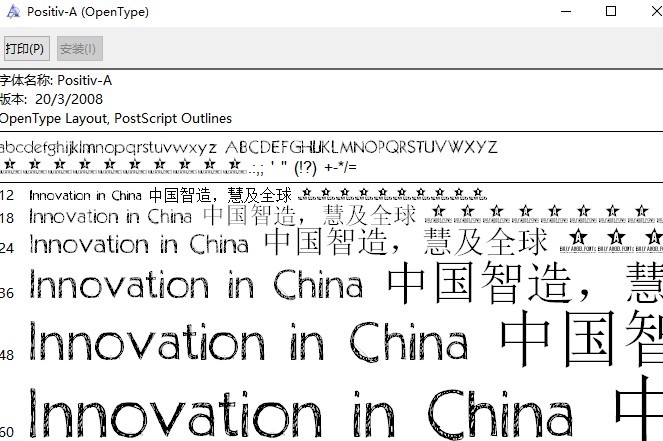
positiva字體是一個(gè)比較有個(gè)性的英文字體。輸出的字體帶有一層浮雕效果,看上去非常大氣。這款英文字體無論是用來設(shè)計(jì)還是排版都很合適。兼容多種主流的計(jì)算機(jī)操作系統(tǒng),喜歡的網(wǎng)友現(xiàn)在就來安裝體驗(yàn)吧!
1.雕刻風(fēng)格特點(diǎn)
2.字體大氣規(guī)范
3.適用范圍廣